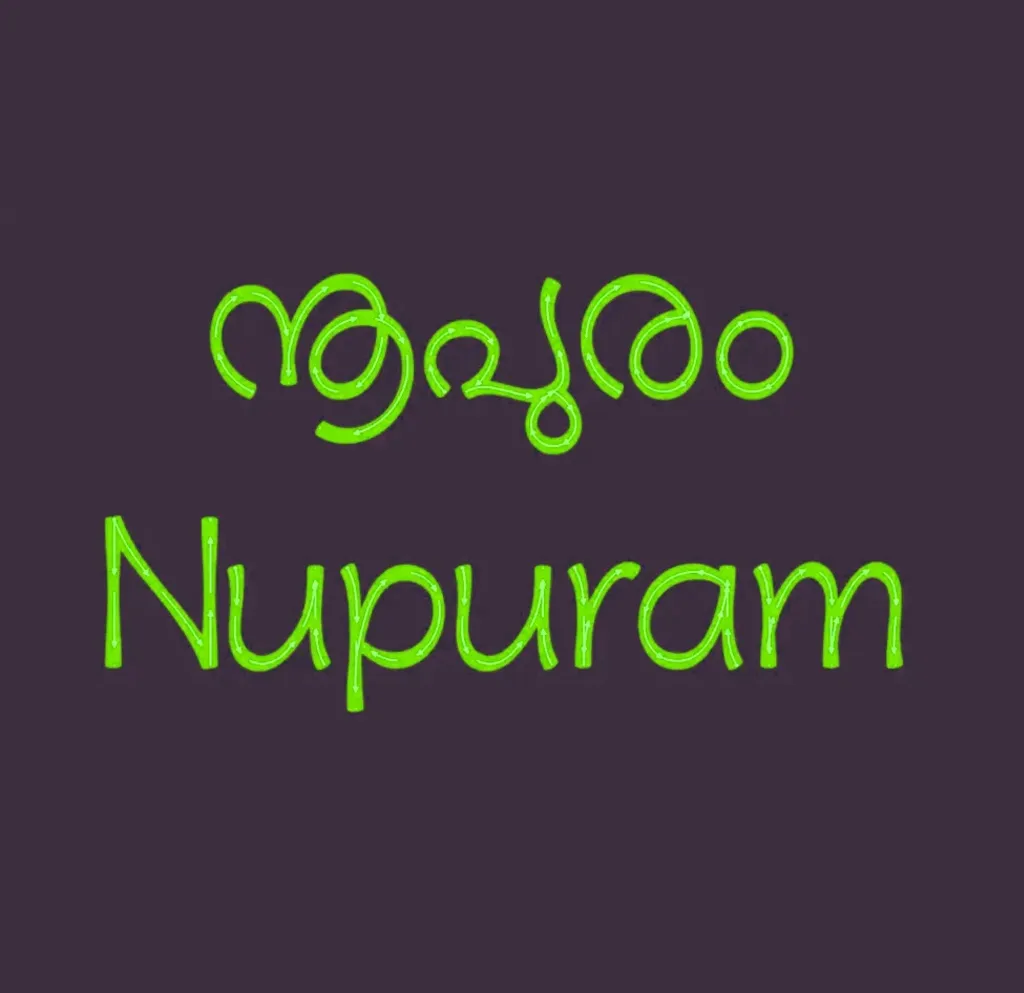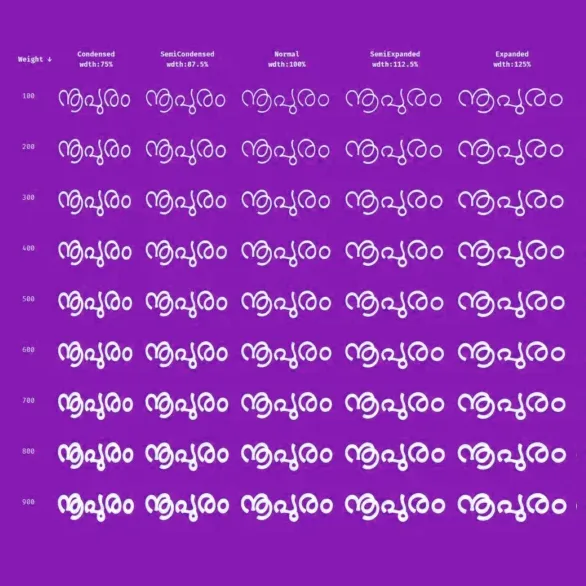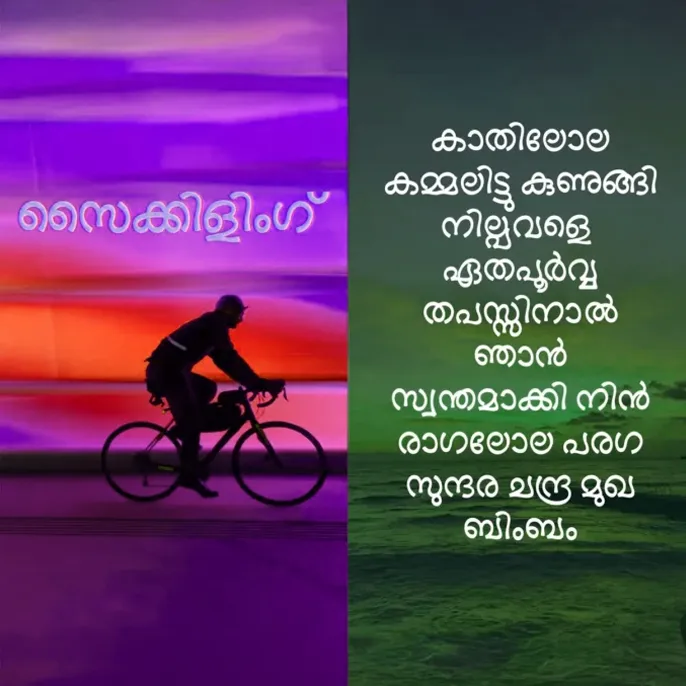
Nupuram | The Most Versatile Variable Malayalam Font Family
മലയാളം ഫോണ്ട് ഡിസൈനിംഗിൽ ഒരു പുതിയ ചരിത്രം കുറിച്ച ഫോണ്ടാണ് Nupuram. പ്രശസ്ത ടൈപ്പോഗ്രാഫി ഡിസൈനർ സന്തോഷ് തോട്ടിങ്ങൽ രൂപകൽപ്പന ചെയ്ത ഈ ഫോണ്ട്, അതിന്റെ വൈവിധ്യം കൊണ്ട് ഏത് തരം ഡിസൈനുകൾക്കും പുതിയൊരു ജീവൻ നൽകുന്നു. സാധാരണ ഫോണ്ടുകളിൽ നിന്ന് വ്യത്യസ്തമായി, അക്ഷരങ്ങളുടെ വണ്ണവും (Weight) വീതിയും (Width) നമുക്ക് ഇഷ്ടാനുസരണം ക്രമീകരിക്കാൻ സാധിക്കുന്ന 'Variable Font' സാങ്കേതികവിദ്യയാണ് ഇതിന്റെ പ്രധാന ആകർഷണം.
പ്രത്യേകതകൾ:
Variable Font Technology: ഒരൊറ്റ ഫയലിൽ തന്നെ നൂറുകണക്കിന് വെയ്റ്റുകളും സ്റ്റൈലുകളും ഉൾക്കൊള്ളിക്കാൻ നുപുരം ഫോണ്ടിന് സാധിക്കുന്നു. ഇത് ഡിസൈനർമാർക്ക് കൂടുതൽ സ്വാതന്ത്ര്യം നൽകുന്നു.
Modern & Calligraphic Touch: ആധുനികമായ സാൻസ്-സെറിഫ് ശൈലിയും പരമ്പരാഗതമായ കാലിഗ്രാഫി അംശങ്ങളും സമന്വയിപ്പിച്ചാണ് ഇത് നിർമ്മിച്ചിരിക്കുന്നത്.
Extensive Styles: Regular, Bold, Condensed, Expanded എന്നിങ്ങനെ അനേകം സ്റ്റൈലുകൾ ഇതിൽ ലഭ്യമാണ്.
Perfect for Branding: ലോഗോകൾ, സിനിമാ ടൈറ്റിലുകൾ, ബ്രാൻഡിംഗ് പ്രോജക്റ്റുകൾ എന്നിവയ്ക്ക് നുപുരം ഒരു പ്രീമിയം ലുക്ക് നൽകുന്നു.
നിങ്ങളുടെ ക്രിയേറ്റീവ് വർക്കുകളിൽ വിപ്ലവകരമായ മാറ്റം കൊണ്ടുവരാൻ Nupuram Malayalam Font തിരഞ്ഞെടുക്കാം.